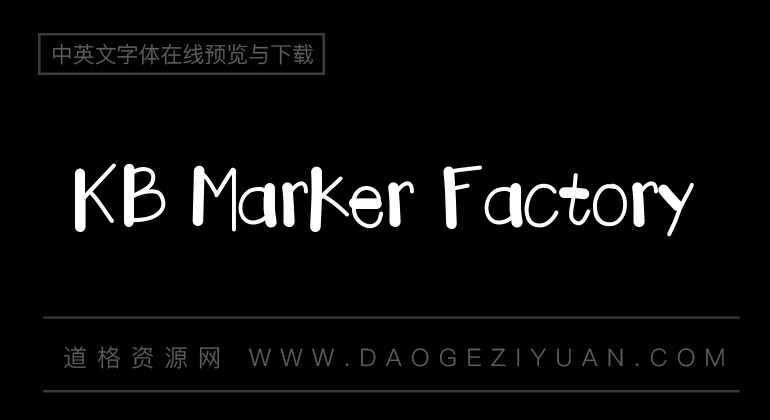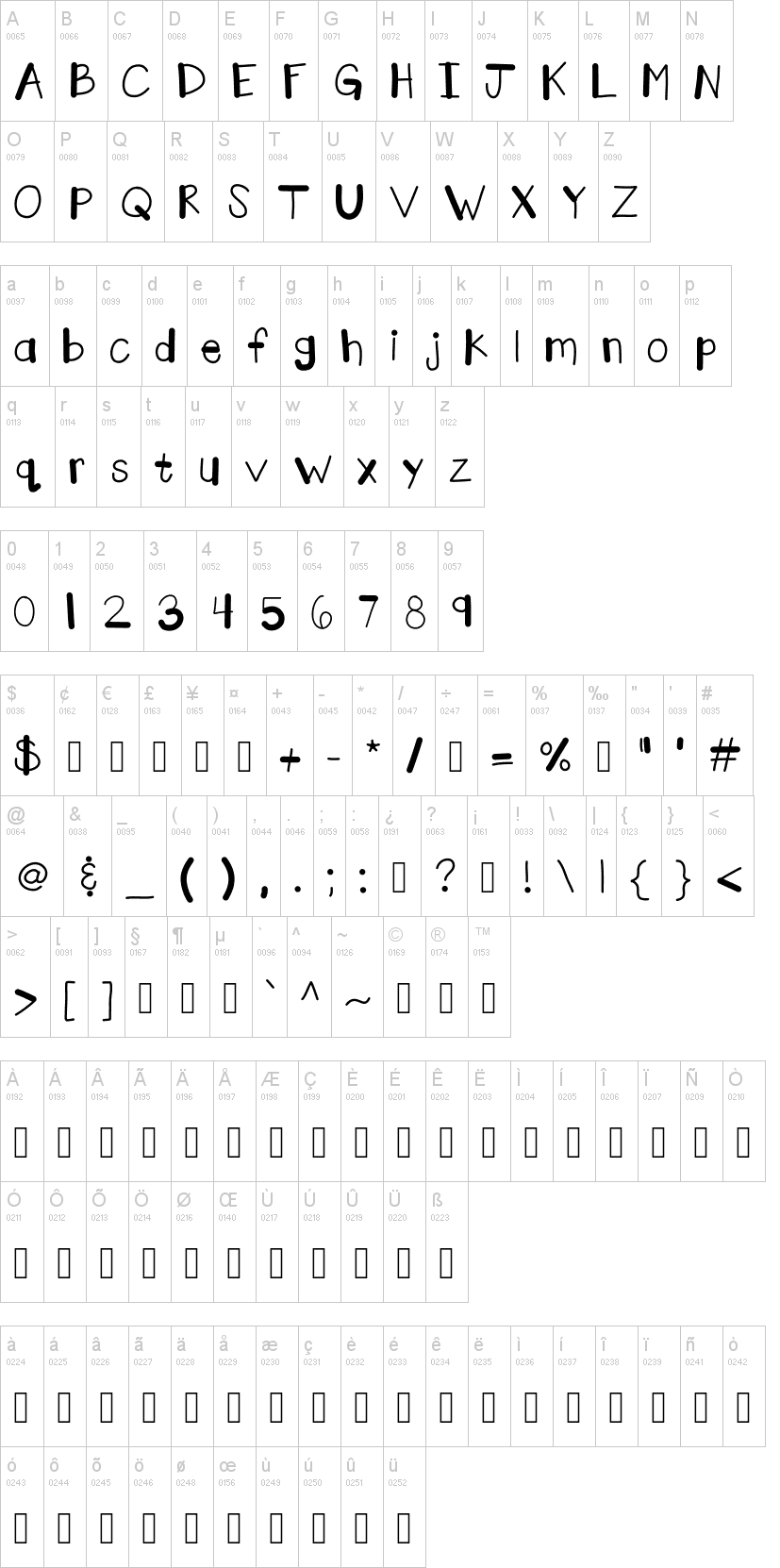
KB Marker Factory 是一种手写风格的字体,它的设计灵感来源于标志和海报上常用的手写字体风格。这种字体的笔画有点粗糙,有时候会有一些不规则的笔画和点,仿佛是手写或手绘的效果。 KB Marker Factory 字体的特点是非常适合用在海报、标题和大型标志设计上。它给人一种非常有个性和创意的感觉,可以强调设计师的创意和个性。与其他手写风格的字体相比,KB Marker Factory 字体的笔画比较清晰,字形也比较规整,这使得它更容易阅读和识别。 KB Marker Factory 字体可以在多种设计项目中使用,例如广告、标志、海报、包装、杂志等,它能够为这些项目带来更加有趣和有创意的效果。内容介绍
KB Marker Factory是一款非常不错的手写艺术字体,具有很好的视觉感,适合于文化类的宣传设计、商业类品牌的广告和产品包装设计以及个性化文字排版等较多场景。